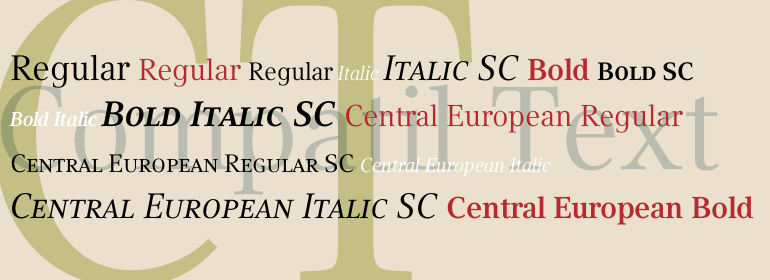
Compatil® Text
Compatil is the first comprehensive type system which enables all typographical elements to be used to full effect in order to reproduce the message conveyed by text information. Four different type styles with a total of 16 weights including italics have been merged into a unique typographical network. There are now no limits to the font user's creativity. The system is a product of technical innovation and constitutes a new design approach which meets the highest aesthetic standards. For almost two years, a team of experts from Linotype has been working with initiator Professor Olaf Leu under the direction of Silja Bilz, Erik Faulhaber and Reinhard Haus to create the Compatil type system. Despite the Internet and TV, it is essential today to be able to absorb information quickly by being able to read it with ease. A fact that is becoming increasingly important both on-screen and on paper. It is the role of the font to increase legibility and to ensure typographically perfect results for text design work. The new Compatil type system meets all these needs. The Compatil is a part of the Platinum Collection.
The following four different styles are available:
Compatil Exquisit,
Compatil Fact,
Compatil Letter and
Compatil Text.